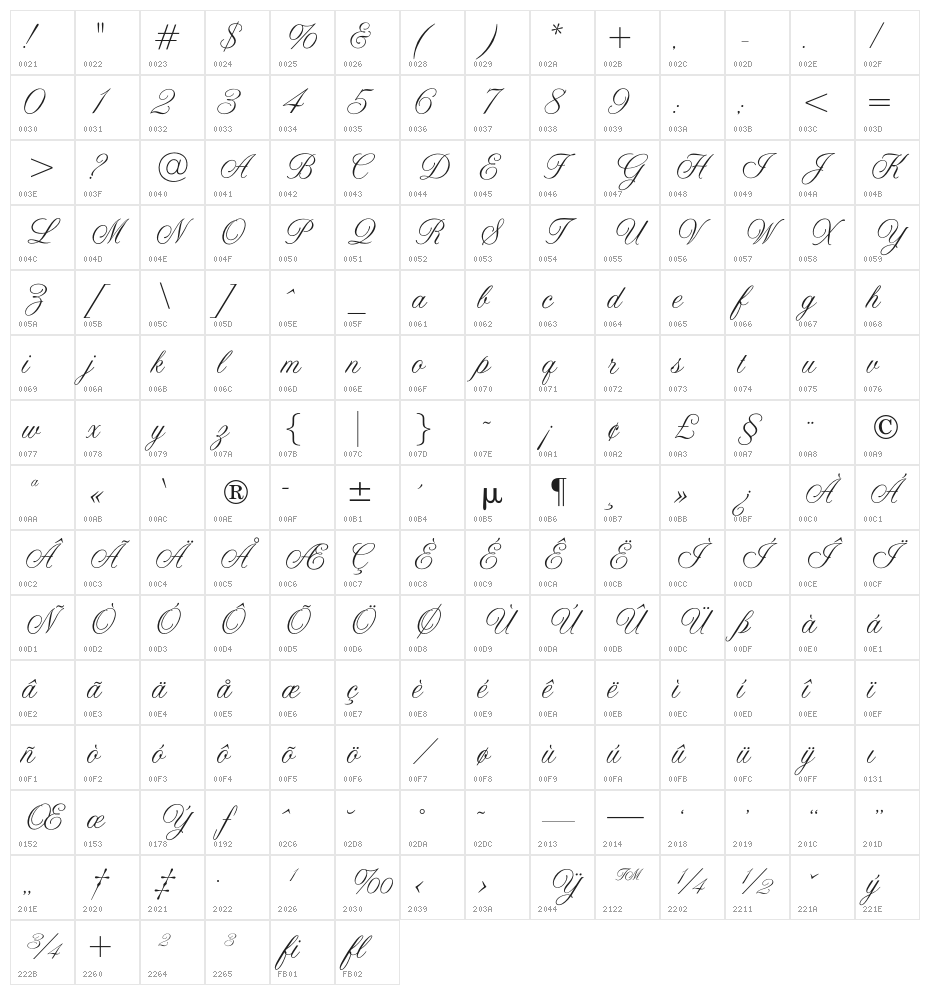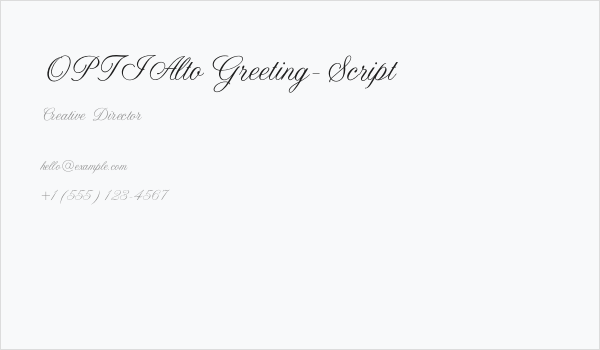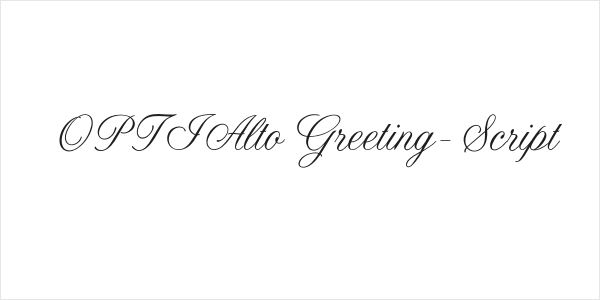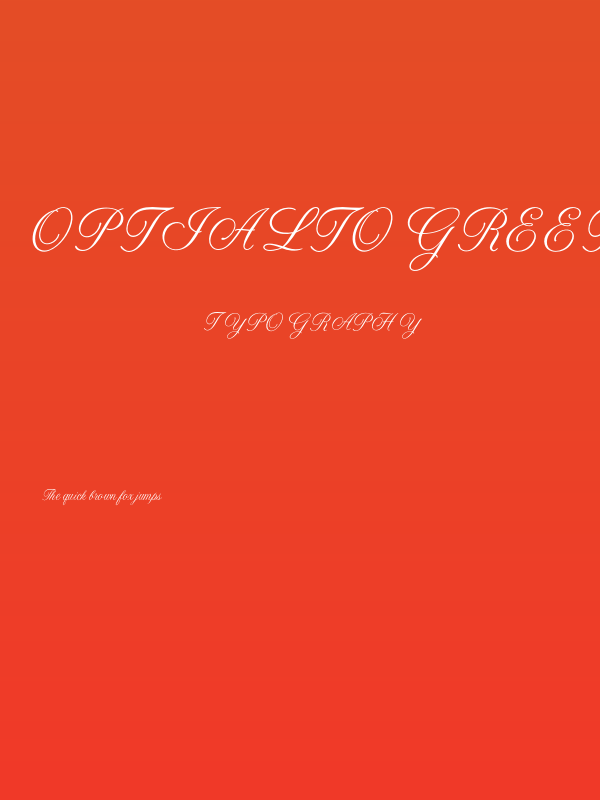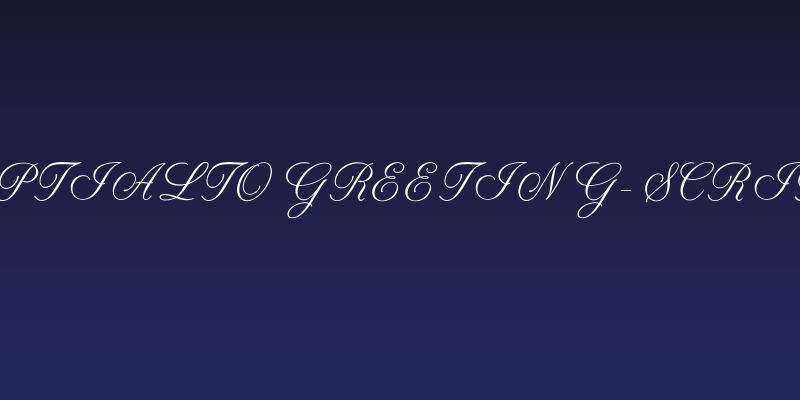
OPTIAltoGreeting-Script Font
| Stile generale | Elegant, Formal |
| Caso d'uso | Logos, Invitations, Decorative text |
| Progetti proposti | Ideal for wedding invitations, greeting cards, elegant branding, and formal event programs. |